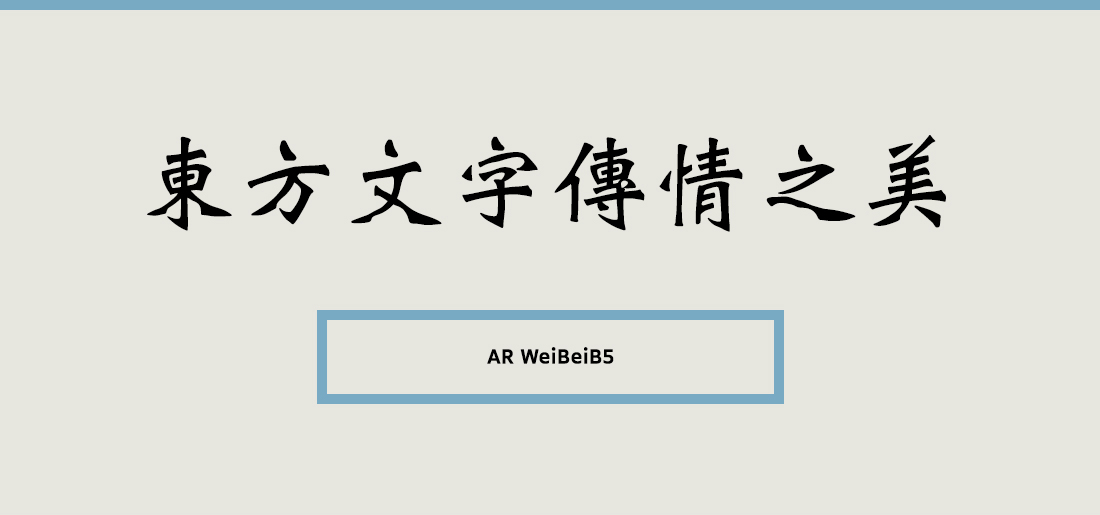
AR WeiBeiB5
WeibeiB5는 단단함 속에서도 부드러운 인상을 주기 위해 탁본의 특징을 가져온 폰트이다.고대 중국 북부 왕조의 탁본에서 영감을 받아 제작되었다.폰트명 뒤에 붙은 B5라는 표기는 번체의 문자코드인 BIG5를 뜻한다. 번체란 중국을 제외한 대만, 홍콩, 마카오 등의 중화권 국가에서 사용하는 전통적인 모양의 한자다. 중국에서 사용하는 간체(GB)와는 달라 잘못 적용할 경우 글립이 제대로 표기되지 않거나 다른 글립으로 표기되는 문제가 발생할 수 있다.